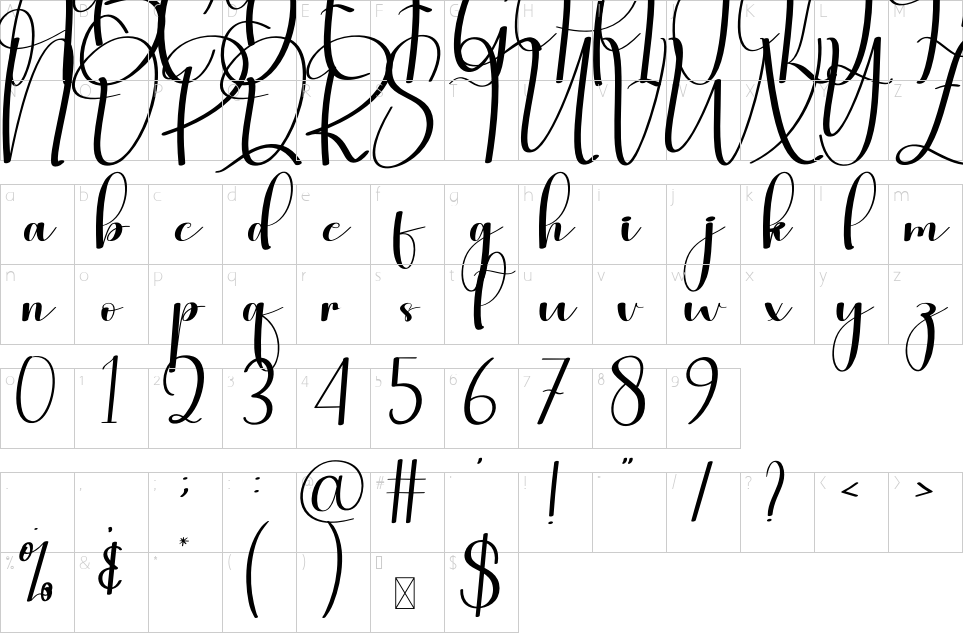
A fonte Mockup é um recurso indispensável para designers gráficos, especialmente aqueles que utilizam o Windows e o Mac. Criada pelo designer William Jhordy, esta fonte foi projetada especificamente para criar uma interface visual chamativa em seu projetos, desde cartões de visita até layouts web. A fonte foi baixada 278 vezes, evidenciando o seu potencial e a sua popularidade entre criadores de conteúdo. Baixe a Mockup font para complementar suas habilidades de design e personalize seu próximo projeto.